「トゲトゲ」な雰囲気にぴったりな日本語フォント
今回は、先端がツンととがった文字や、鋭い装飾が目を引く「トゲトゲ」な雰囲気の日本語フォントをご紹介します。
シャープでスマートな力強さを出したいときも、薔薇のような妖しい美しさを表したいときも、文字のトゲが印象づくりのアクセントになります。トゲの大きさや線の太さによって、攻撃的にも、繊細にも、可愛くも見せられるのが面白いところです。
いいフォントで紹介している書体から、尖った装飾や鋭い角が特徴の15種類をピックアップしました。ロゴやタイトル、動画の字幕など、文字を主役にしたい場面に合わせて選んでみてください。
「トゲトゲ」なデザインにおすすめの日本語フォント
トゲトゲロック
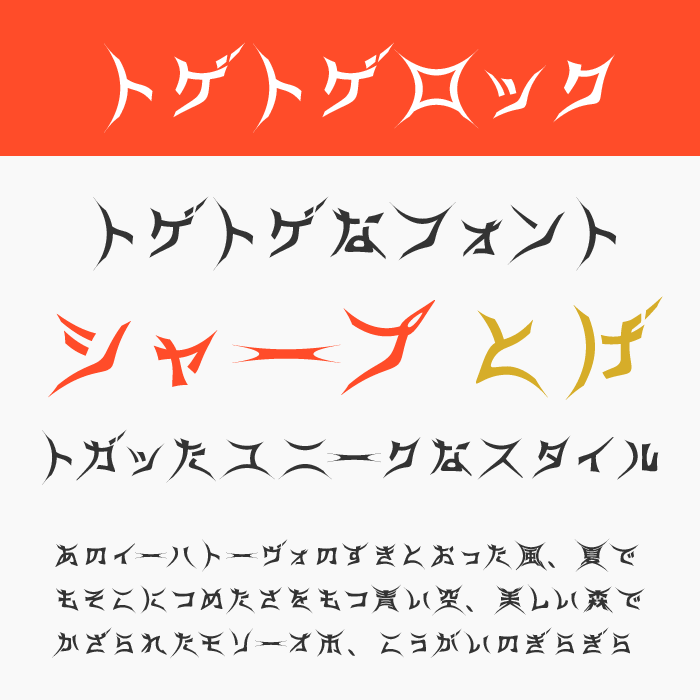
トゲトゲロックは、文字の上下左右から鋭いトゲが突き出した、力強いデザインフォントです。
外側へ引っ張られたような形が、ひと言のタイトルにも強い存在感を与えます。ライブの告知やパンクなステッカー、荒々しいキャラクターの名前にぴったり。短い言葉を大きく組み、周囲に余白を残すと、トゲの先端までしっかり見せられます。黒一色でも迫力を出しやすい一本です。
トガリテ
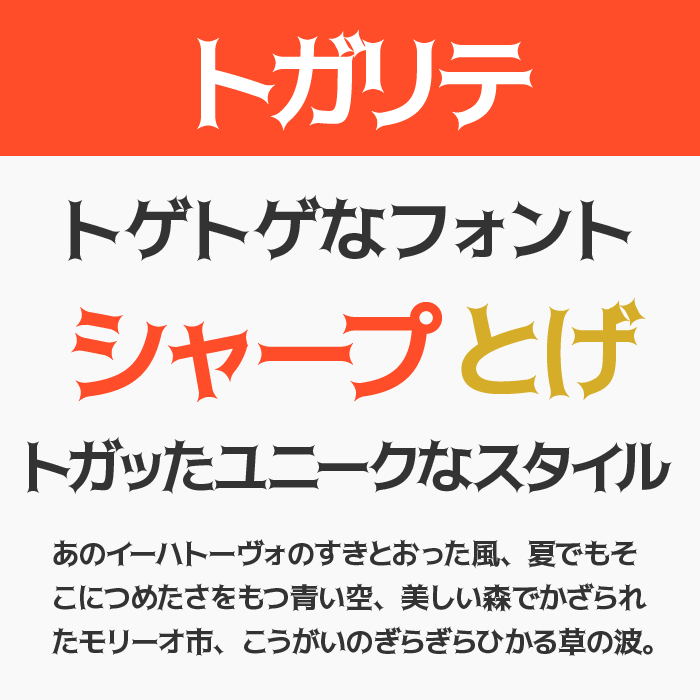
トガリテは、文字の先端にとがった装飾を加えた、シャープさと親しみやすさをあわせ持つフォントです。
細かなトゲがアクセントになるので、攻撃的になりすぎず、少し個性のある文字を使いたいときにおすすめ。7種類の太さがあり、細めなら軽やかに、太めならポップで力強く見せられます。ファッションの見出しやイベント名など、普段のゴシック体から印象を変えたい場面で活躍します。
イバラ字
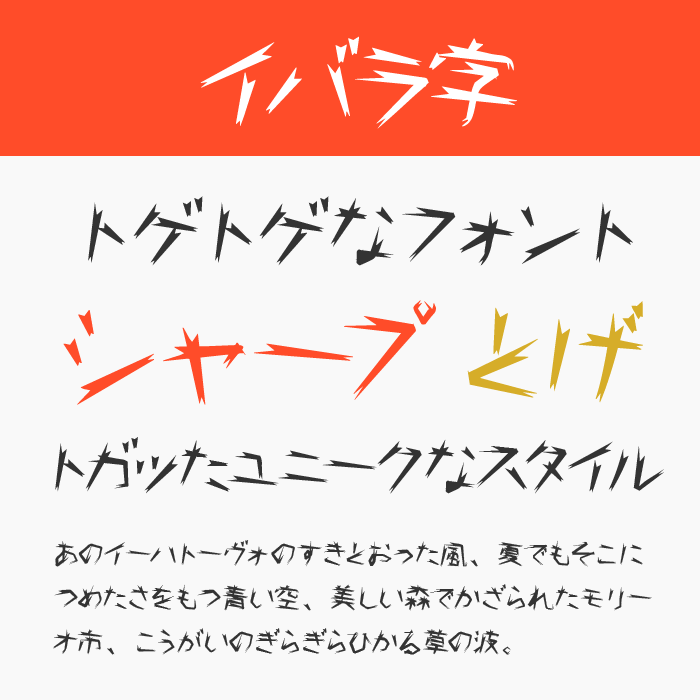
イバラ字は、植物のいばらを思わせる鋭い先端と、勢いのある字形が特徴のフォントです。
文字が跳ねるように見えるため、怒ったセリフや強いツッコミに使うと、声の調子まで伝わりそうです。マンガの吹き出しだけでなく、動画の字幕や刺激を感じさせたい商品の見出しにもおすすめ。無料版は漢字の収録範囲が限られるので、使いたい文言がそろうか確認してから組んでみてください。
棘薔薇フォント
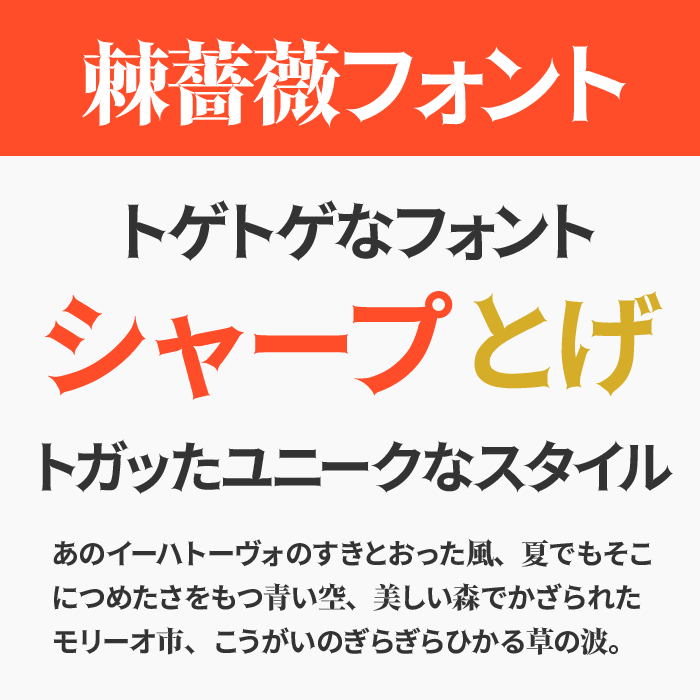
棘薔薇フォントは、薔薇のトゲのような装飾が文字の先に伸びる、華やかなフォントです。
鋭さの中に優雅さがあり、荒々しいロック調とはひと味違う「トゲトゲ」を楽しめます。薔薇やレースを使ったデザイン、少し妖しい物語の表紙などにおすすめ。3種類の太さを比べながら選ぶと、繊細な雰囲気から存在感のある見出しまで、場面に合わせた表情を作れます。
黒薔薇ゴシック
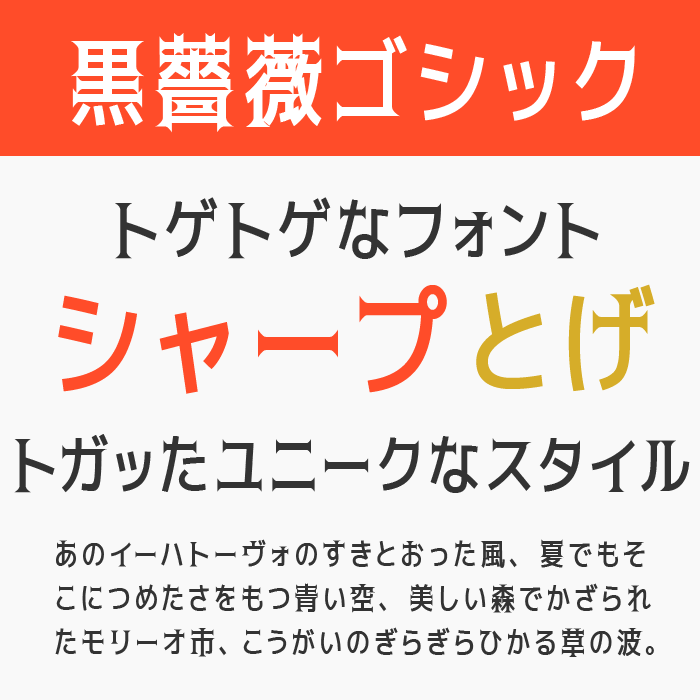
黒薔薇ゴシックは、ゴシック体をもとにトゲの装飾を加えた、華やかで少し危うい雰囲気のフォントです。
整った文字の骨格に鋭い飾りが付くことで、可愛らしいモチーフにもダークな表情を添えられます。ゴシックロリータの告知や、秘密を感じさせる作品タイトルによく合いそうです。7種類の太さがあるので、背景の情報量や文字の大きさに合わせて、装飾が見えるものを選びましょう。
黒薔薇シンデレラ&赤薔薇シンデレラ
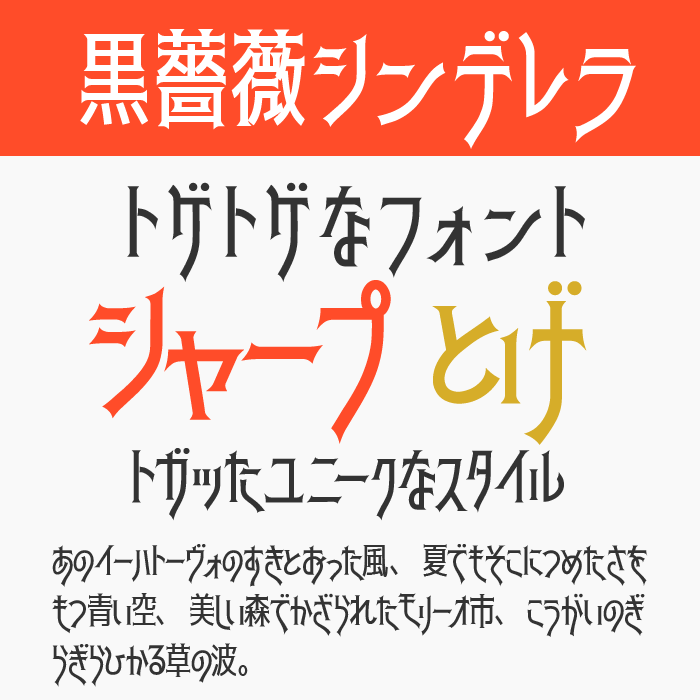
黒薔薇シンデレラと赤薔薇シンデレラは、縦長の文字にトゲのような装飾をまとわせたフォントです。
細長いシルエットが、童話の城や夜の舞踏会を思わせる雰囲気に似合います。2種類は文字の比率や飾り方が異なるため、同じタイトルを入力して見比べるのがおすすめ。花や王冠などのモチーフを添える場合も、文字のトゲとぶつからないように間隔を空けると、上品にまとまります。
棘丸ゴシック
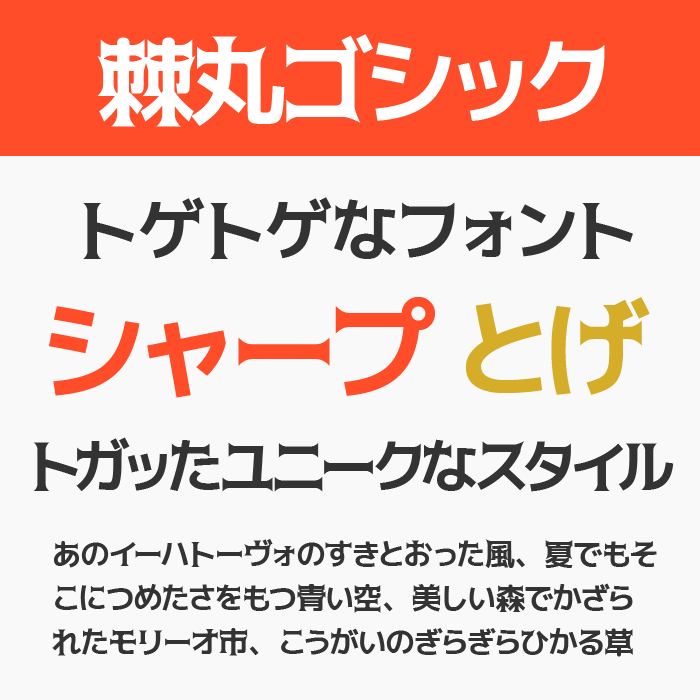
棘丸ゴシックは、鋭いトゲと丸い点の装飾を組み合わせた、遊び心のあるゴシック体です。
とがった部分だけでなく丸いパーツも目に入るので、怖さよりも、可愛さと強さを両立させたいデザインに向いています。元気なキャラクターの名前や、パンチのあるイベントロゴにおすすめ。7種類の太さから選べるため、小さめの見出しでは飾りがつぶれない太さを試すとよいでしょう。
レゲエOne(Reggae One)
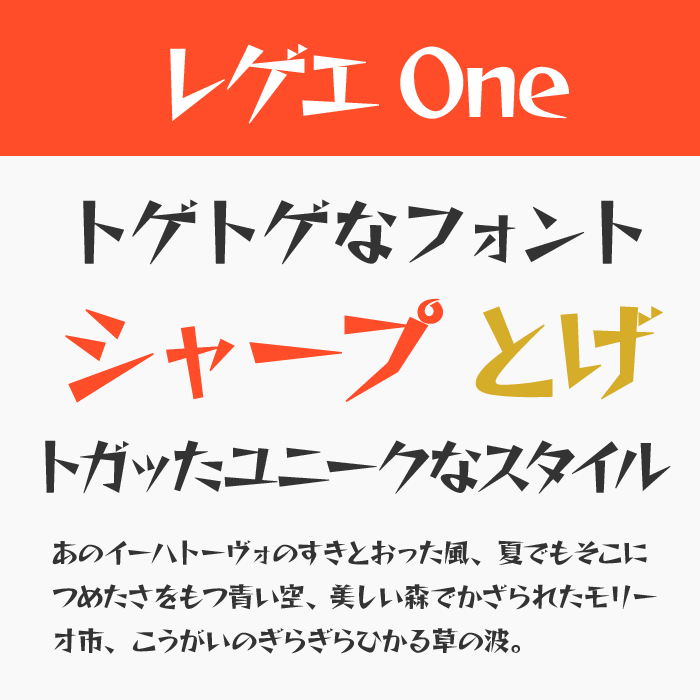
レゲエOneは、先端が鋭く伸びた文字に動きが感じられる、エネルギッシュなフォントです。
文字の一画一画に勢いがあり、驚きや怒りを表す短い言葉と好相性。アクションもののタイトルや動画の強調字幕など、見た瞬間に熱量を伝えたい場面におすすめです。長文をすべてこの書体にするより、ここぞというひと言に使うと、とがった形が効果的なアクセントになります。
ストロングガール
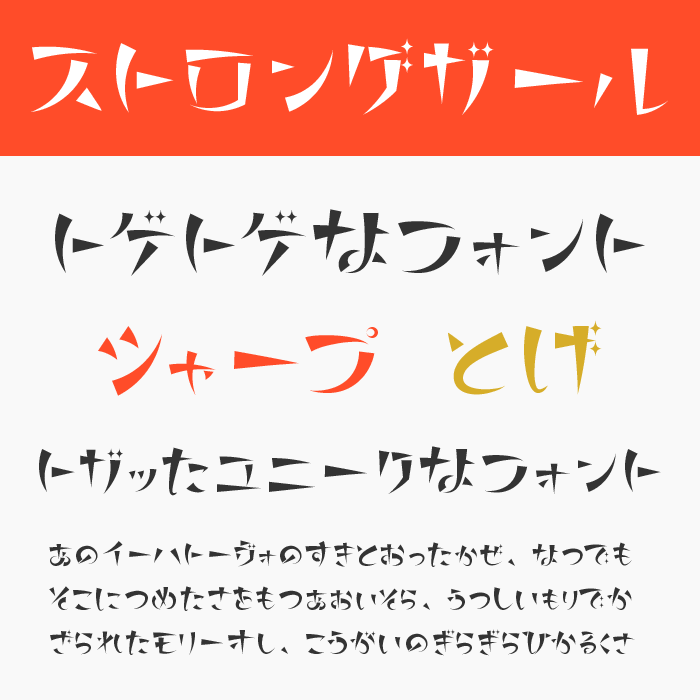
ストロングガールは、鋭い字形ときらめくような濁点が印象的な、強さと可愛さを感じるフォントです。
ちょっと生意気なセリフや、元気なカタカナのロゴに使いたくなるデザインです。明るい色を合わせればポップに、モノトーンならクールな表情に見せられます。無料のSideAにはひらがなが入っていないため、まずはカタカナや英字の短い名前から試してみると使いやすいでしょう。
柊の葉っぱフォント
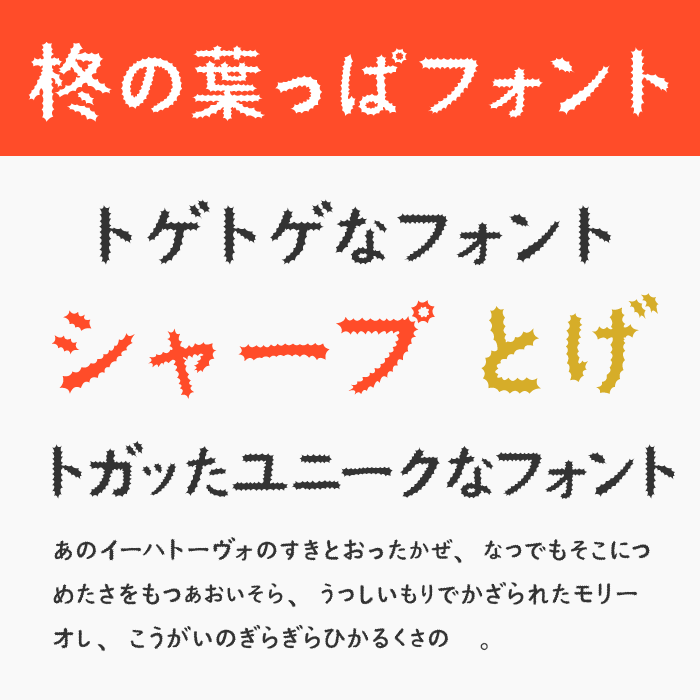
柊の葉っぱフォントは、ヒイラギの葉のように、文字の周囲へ小さなトゲが広がるフォントです。
葉っぱを思わせる形には少し丸みもあり、トゲがあっても親しみやすい表情に仕上がります。クリスマスのカードや植物をテーマにした見出しなど、季節感を文字にも取り入れたい場面におすすめ。漢字は「葉」「柊」のみなので、かなを中心にしたタイトルを考えると持ち味を活かせます。
g_コミックホラー悪党
g_コミックホラー悪党は、文字の周りに鋭い突起が付いた、毒々しい雰囲気のフォントです。
悪役が低い声で話す場面や、相手を威圧するひと言など、不穏な感情を乗せたいときにぴったり。尖った輪郭が強く主張するので、短いセリフでも印象に残ります。文字を詰めすぎると隣のトゲと重なりやすいため、間隔を少し調整しながら、輪郭が分かる大きさで使うのがおすすめです。
叛逆明朝(Hangyaku)
叛逆明朝は、細く鋭い先端と伸びやかな装飾を持つ、妖しさのある明朝体です。
針のような線が、重厚なトゲの書体とは違う繊細な緊張感を生みます。魔女や夜の街を描く表紙、華やかさの裏に危うさがあるロゴなどにおすすめ。細部が見える大きさで使うと魅力が伝わります。宗教・政治等に関する用途制限も案内されているので、作品の内容に応じて配布元の規約を確認してください。
金畫字(キンカクジ)
金畫字は、直線と三角形のパーツが組み合わさった、硬く鋭い印象のデザインフォントです。
植物のトゲというより、金属を切り出したような角の鋭さを楽しめる一本です。武器や組織の名前、力強さを出したいタイトルなどによく合います。背景をシンプルにして文字を置くと、斜めの線や三角形が際立ち、輪郭だけでも印象的なロゴ風の見せ方ができます。
ヘキサデビル
ヘキサデビルは、六角形をもとにした角張った字形が特徴の、ダークファンタジー向けフォントです。
細いトゲを足すタイプとは異なり、文字そのものの鋭い角で緊張感を出せます。短いカタカナを並べると、不思議な記号のようにも見えるため、呪文や必殺技の名前におすすめ。商用利用には作者指定のSNSをフォローする条件があるので、利用前に配布ページの案内を確認しましょう。
Chokokutai(彫刻体)
Chokokutaiは、細い線と鋭い角が、素材へ彫り込んだ文字を思わせるフォントです。
大きなトゲで迫力を出す書体とは違い、線の細さが静かな鋭さを感じさせます。工芸やアクセサリーの見出し、ひんやりとした雰囲気のタイトルにおすすめ。かなや英字で短く組み、周りに余白を取ると、彫刻刀の跡のような輪郭が見えやすくなります。漢字を使う部分は別の書体と組み合わせましょう。
トゲトゲしたフォントは、先端の形が見える大きさで使うと魅力が伝わります。力強く見せたいなら太い文字、妖しく上品に見せたいなら細い装飾など、伝えたい雰囲気に合わせて選ぶのがおすすめ。文字の周りに余白を残し、トゲの形を楽しんでみてください。